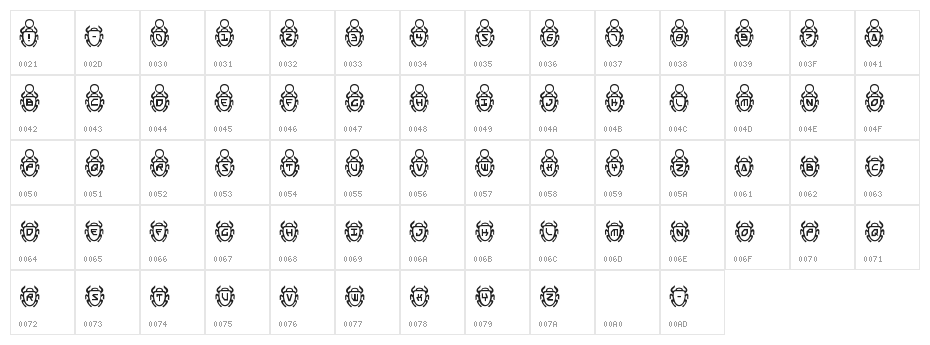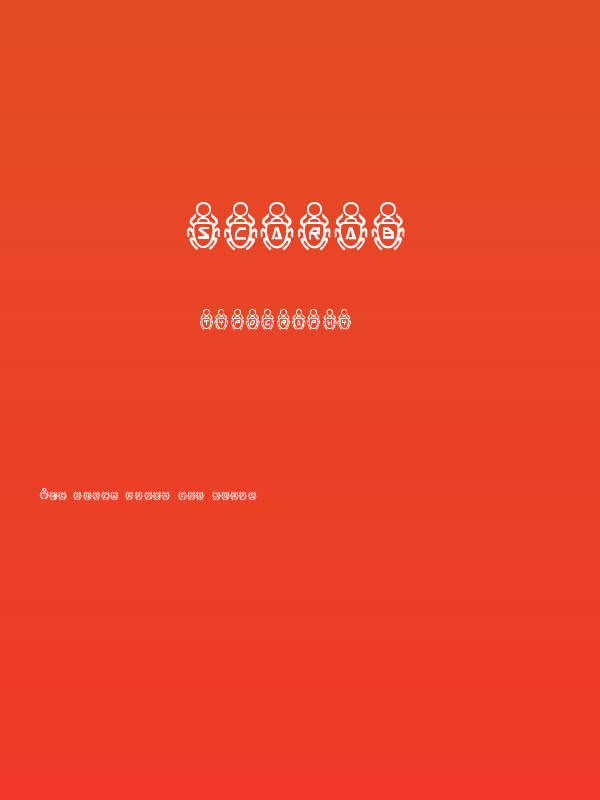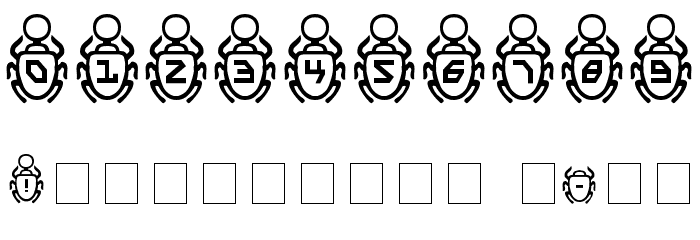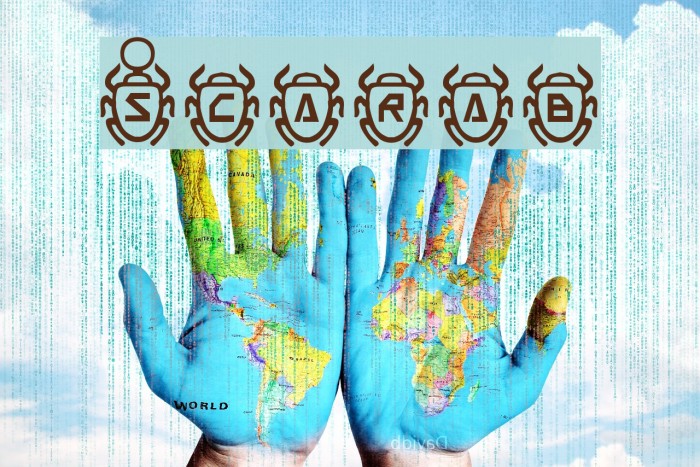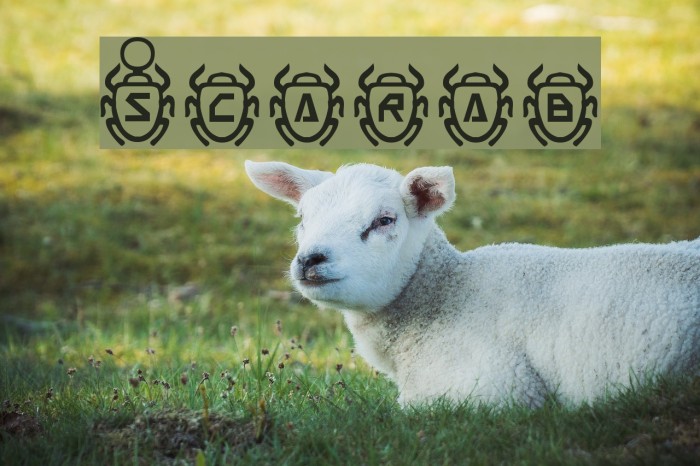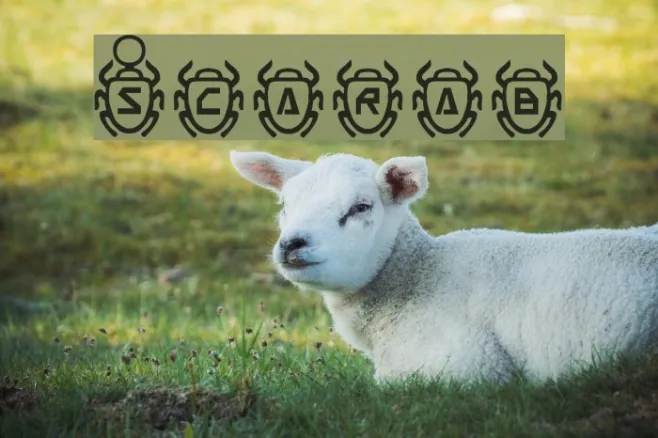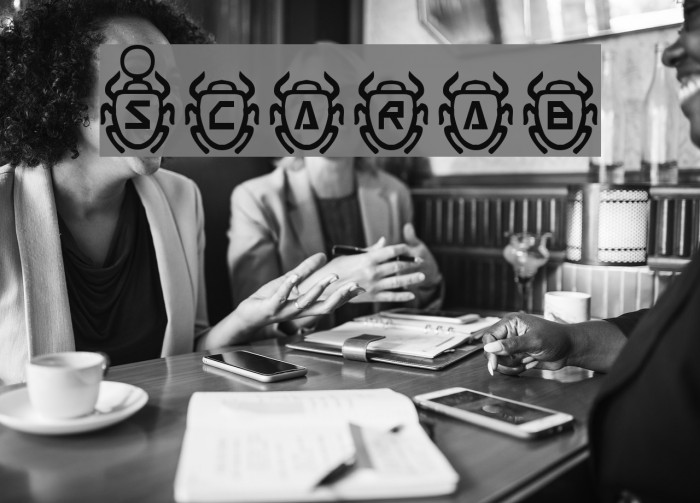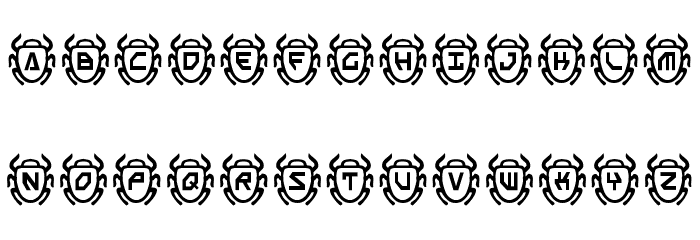
Scarab Font
| Anwendungsfall | Logos, Artistic displays, Themed events |
| Vorgeschlagene Projekte | Ideal for themed events, logos, artistic displays, and creative branding. |